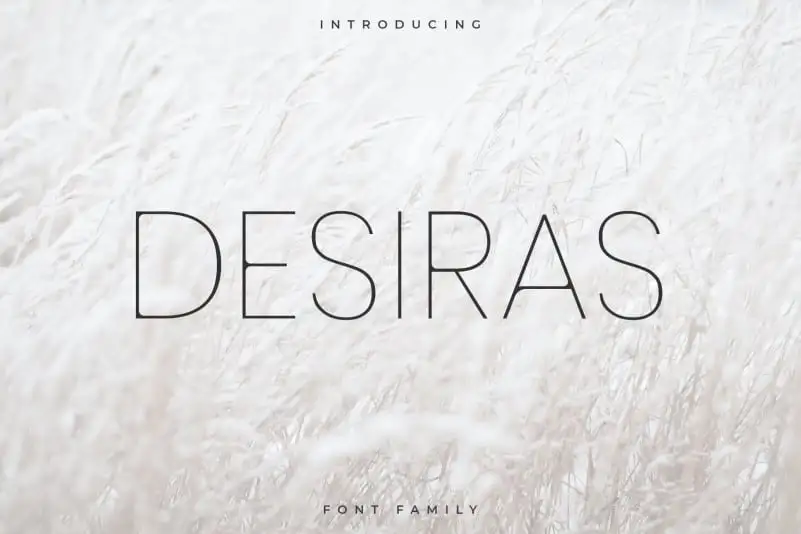
Desiras Sans Serif Font – Download Grátis
A Desiras Sans Serif é uma moderna tipografia sans-serif projetada para se destacar tanto no uso de cabeçalhos quanto em grandes trechos de texto. Ela foi criada pelo designer fonte Robin Campistron e incorpora características minimalistas, que a tornam uma fonte serifless perfeita para ambientes onde você deseja um design limpo e contemporâneo, seja em layouts, seções de destaque ou qualquer projeto web. Com quatro diferentes pesos, esta elegante fonte é perfeitamente adaptável para uso em designs de revistas, cartões de convite ou outros projetos. Suas formas geométricas e silhuetas leves fazem dela uma opção ideal para ambientes onde se deseja destacar a legibilidade e modernidade do design, mesmo em grandes tamanhos e com pouca profundidade tipográfica. A Desiras Sans Serif oferece um contraste visual perfeito entre o texto grande e os detalhes menores, proporcionando uma experiência de leitura suave ao cliente final. Seja você criador de cartazes, designer de logotipos ou até mesmo produtor de conteúdo web, a Desiras Sans Serif é um investimento valioso para tornar suas criações ainda mais visíveis e atraentes.